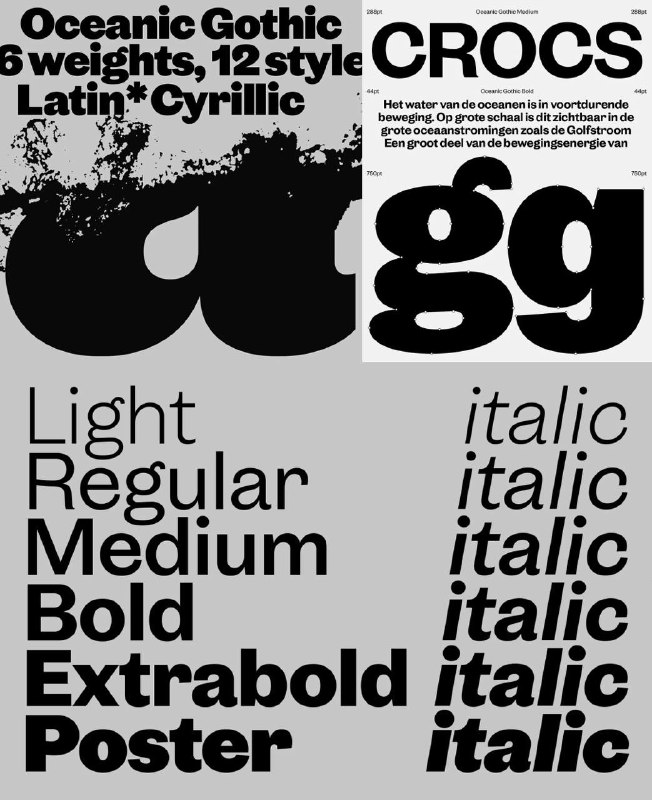
Oceanic Gothic — гуманистический гротеск
Oceanic Gothic. Выразительный гуманистический гротеск с лёгкой декоративностью и винтажным характером. Содержит шесть вариантов насыщенности с курсивом для каждого и вариативный шрифт.
Подойдёт как для заголовков, так и для более мелкого текста. Будет хорошо смотреться в оформлении сайтов или брендинге.
Образец шрифта Oceanic Gothic: постер с демонстрацией шести насыщенностей, латиницей и кириллицей, заголовочными формами и курсивами для брендинга и веб‑оформления.
Презентация семейства Oceanic Gothic с образцами начертаний и курсивов.